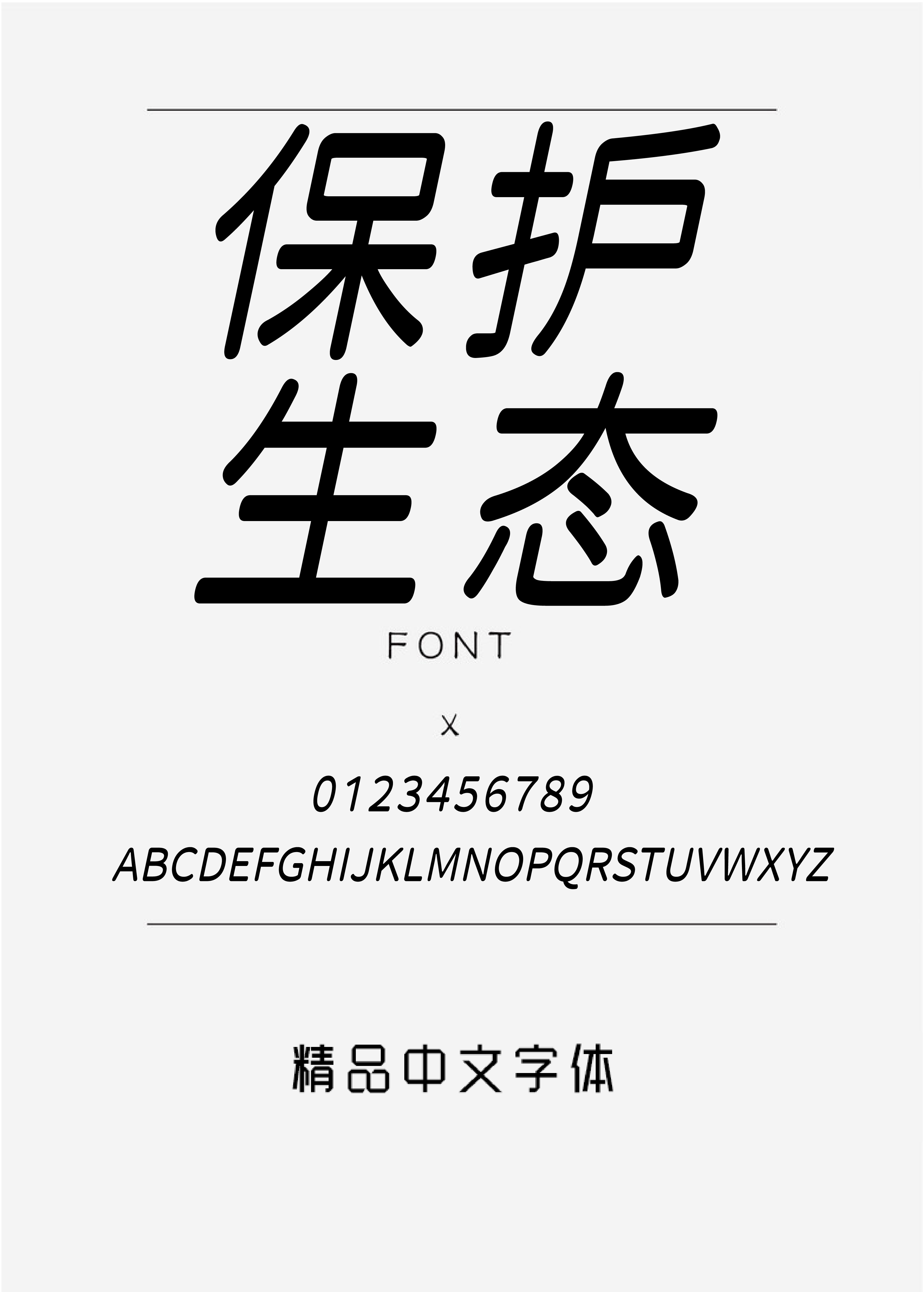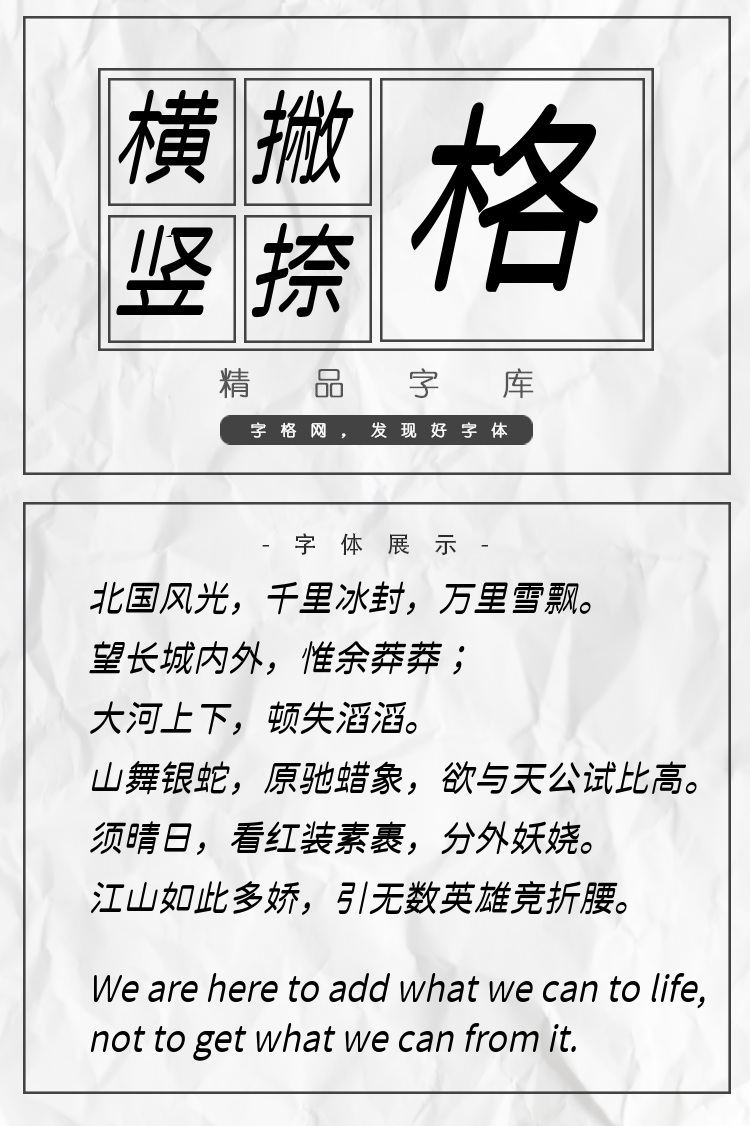
江城月湖体斜体中文字体500W
字体说明:江城月湖体斜体中文字体500W字体是一款可商用的毛笔书法,英文手写,手写体字体,该字体包含6763个中文、字母、符号和数字,具有充满力量、大气、豪放、稳重、手写风、古典 的风格,可以满足您设计上的各种需求,该字体主要用于电商、广告、视频影视、海报企宣、书籍 等场景, 您不但可以在字格网下载江城月湖体斜体中文字体500W,同时还有众多毛笔书法字体、创意字体等可供选择!